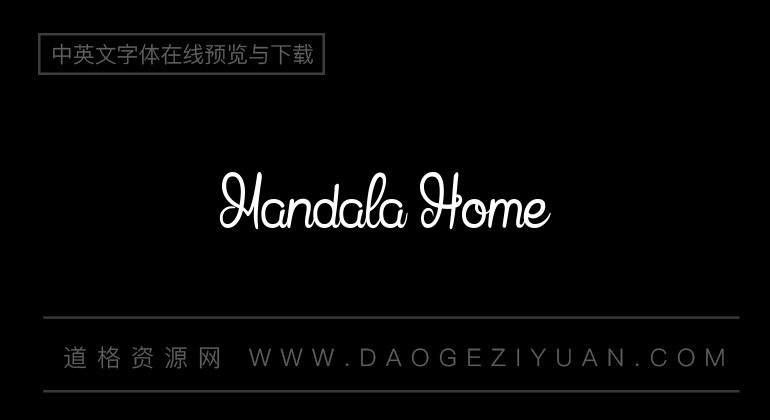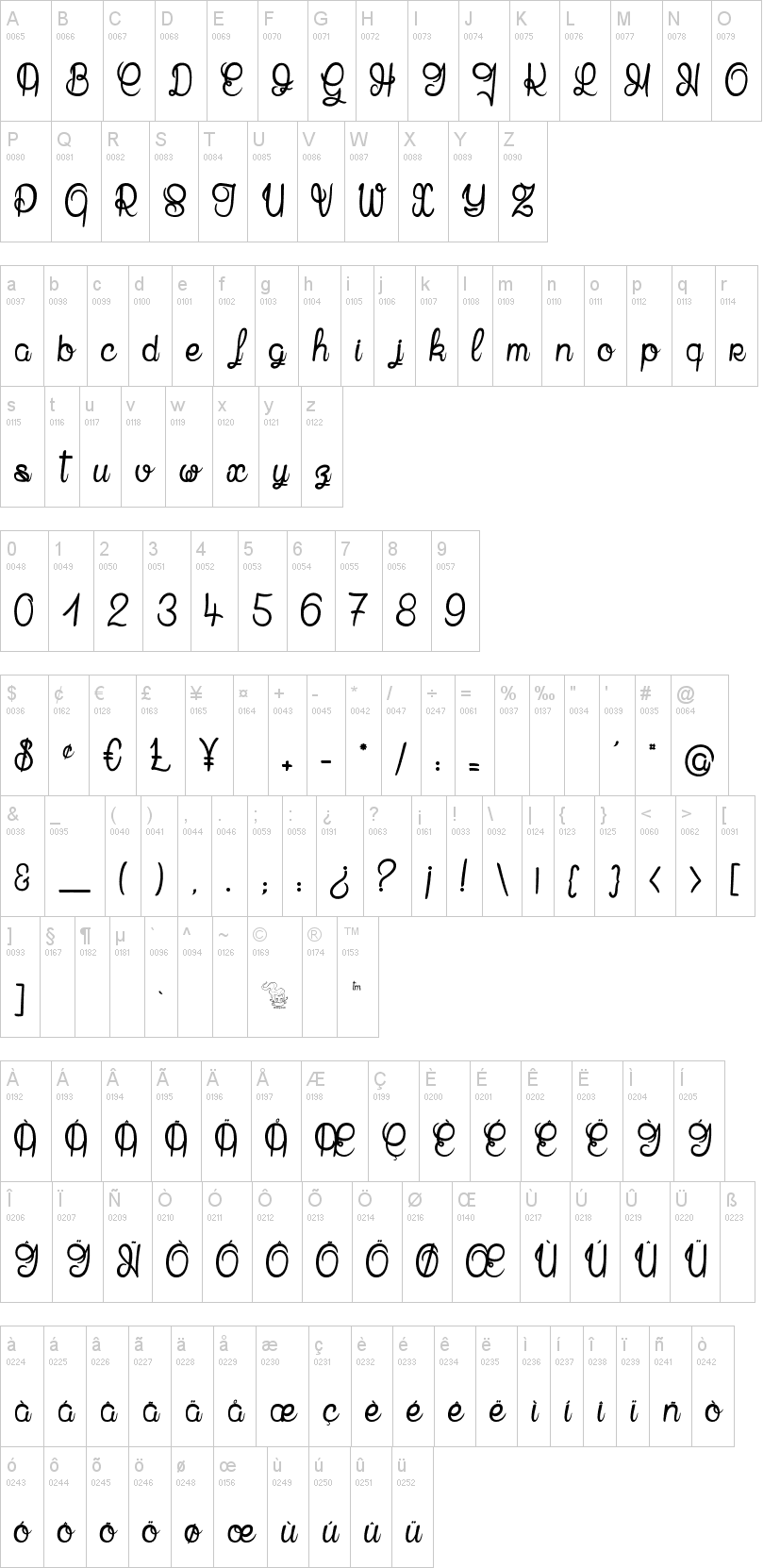
Mandala Home 字体是一种具有独特的设计风格的字体,它可以用于个性化的文本和图片设计,以及手绘艺术创作。它具有细腻的线条,曲线,点状,以及抽象的图案,可以提供一个充满活力的视觉效果。Mandala Home字体适合用于品牌标识,海报,卡片,标签,网页,图书封面等设计项目。内容介绍
Mandala Home是一款非常不错的手写艺术字体,具有很好的视觉感,适合于文化类的宣传设计、商业类品牌的广告和产品包装设计以及个性化文字排版等较多场景。